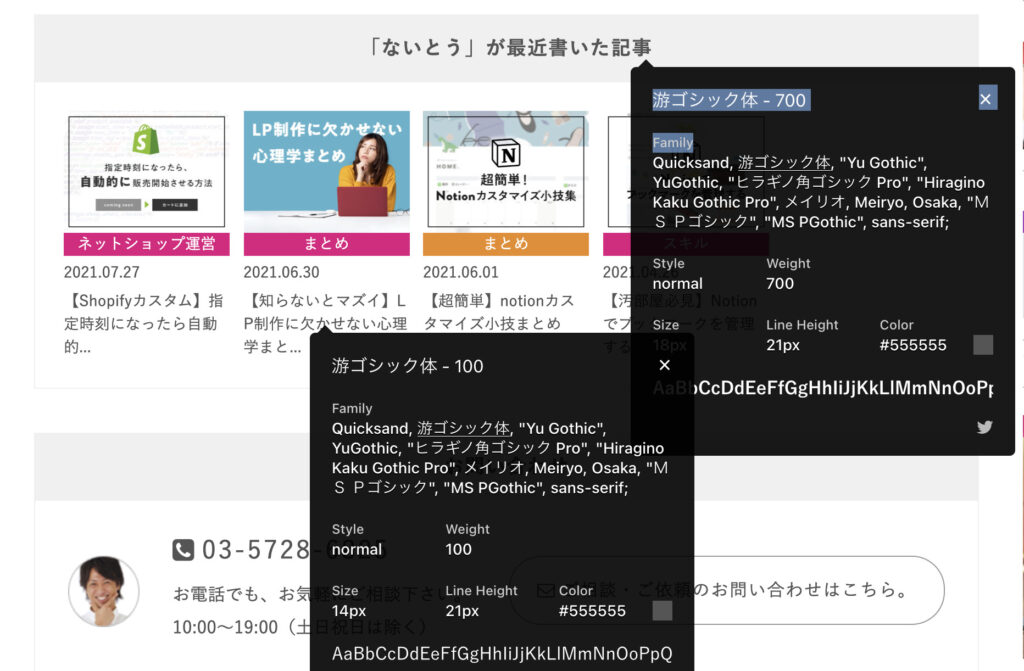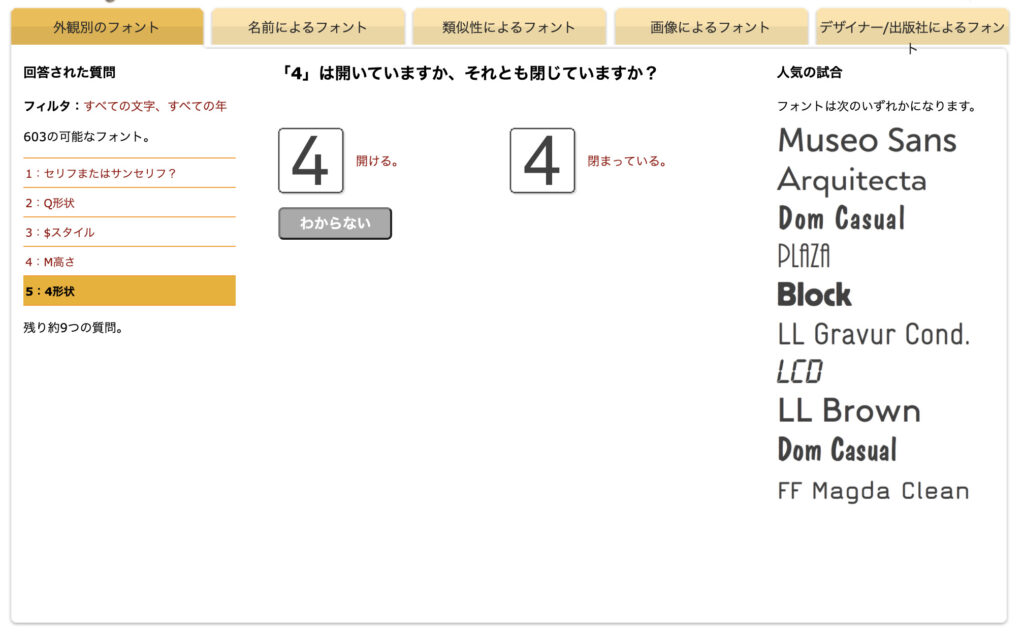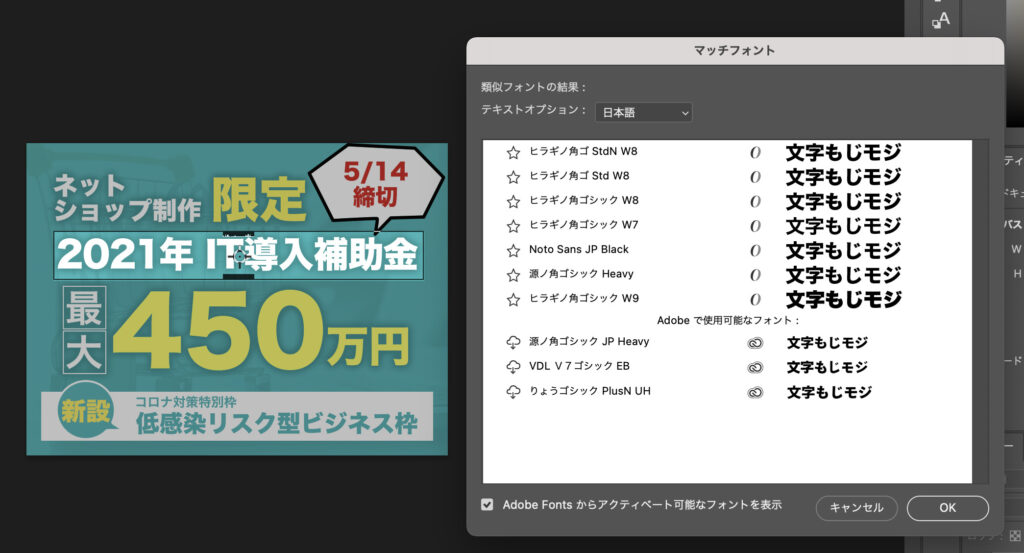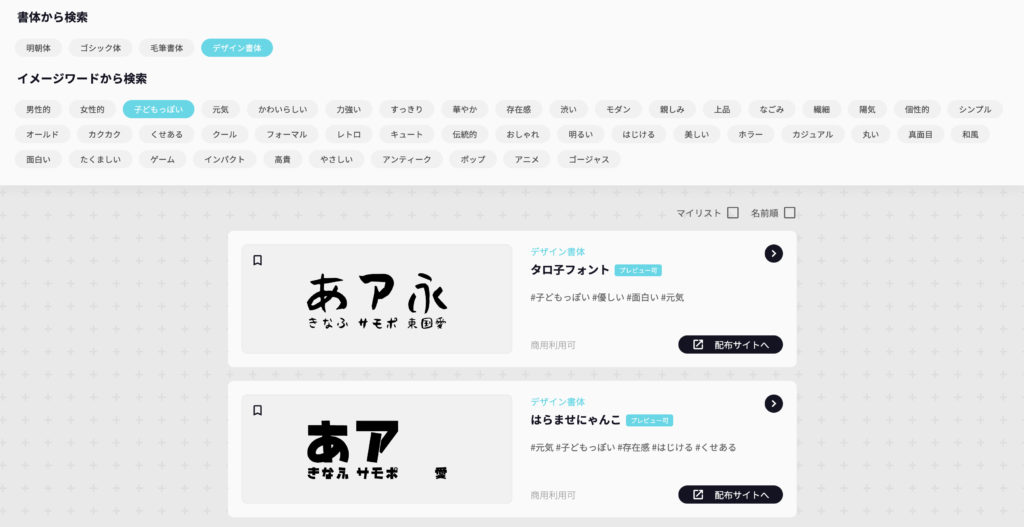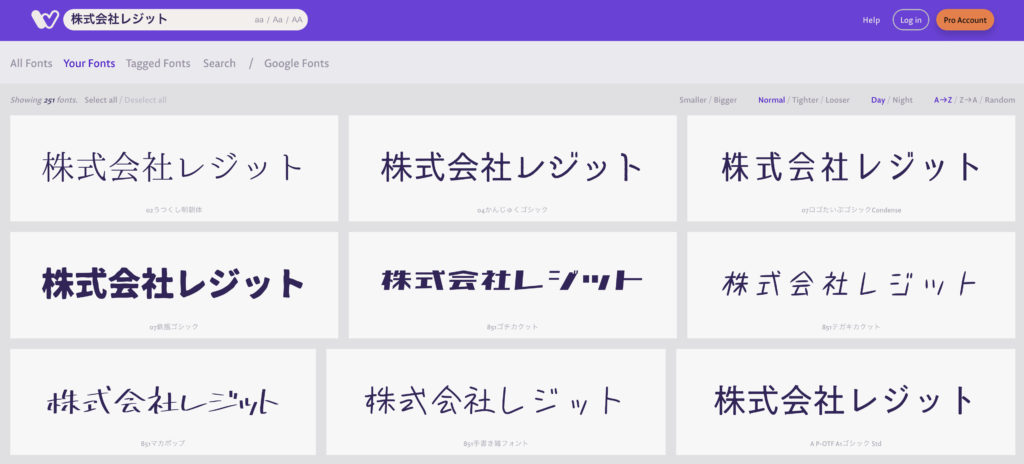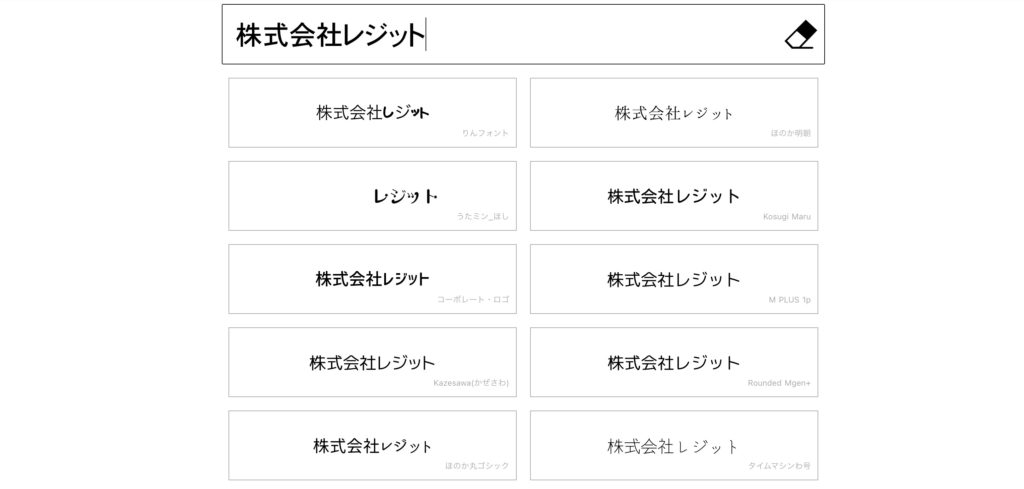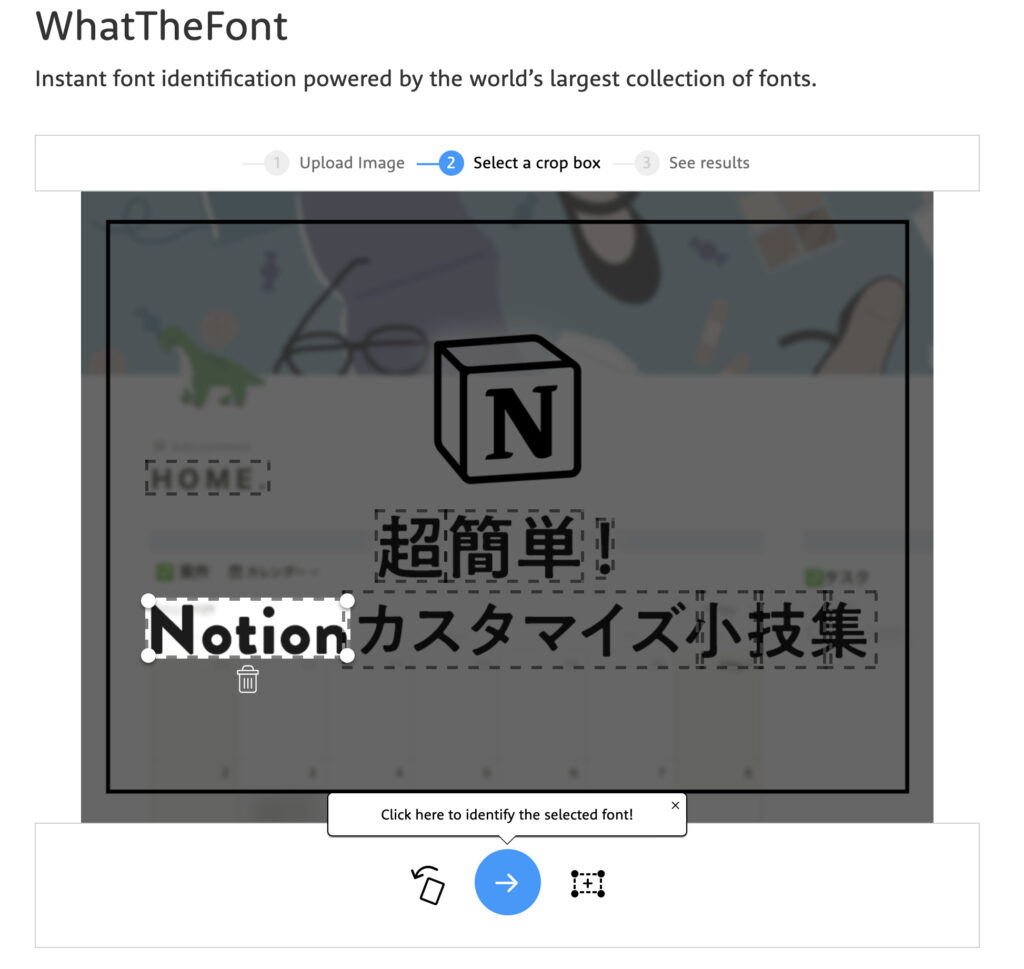
フォントを検索・特定する方法|画像・Webサイト・日本語の調べ方
フォントを検索・特定するときは、最初に「画像の文字」「Webページの文字」「似た書体を選びたい」のどれかを分けます。画像用の検索ツールと、Webページの文字を調べるツールでは、できることが異なります。
この記事では、2021年公開の内容を編集部が確認し直し、画像検索、ブラウザでの確認、試し書きの使い分けを整理しました。候補が見つからないときの見直し方や、利用前の確認も紹介します。料金、対応言語、ログイン条件は変更されることがあるため、各公式案内も確認してください。
調べたい文字の状態で方法を選ぶ
選択できるテキストならブラウザ、写真やスクリーンショットなら画像検索が出発点です。まだ名前が分からず雰囲気から探したいときは、候補の試し書きを比べます。
| 調べたいもの | 使う方法 | 確認できることの目安 |
|---|---|---|
| 写真・スクリーンショット | WhatTheFont、Photoshop | 画像に近いフォントの候補 |
| Webページのテキスト | WhatFont、Chrome開発者ツール | 指定された書体や実際の表示書体 |
| 日本語の候補を見比べたい | ためしがき等の試し書き | 入力した文字の形と雰囲気 |
画像検索で名前が出ても、元の書体が確定したとは限りません。変形、縁取り、文字間隔などが加わっている可能性もあるため、同じ文字列で照合します。
画像から候補を探す方法
画像の中の文字は、フォント名を含むテキスト情報として調べられないことがあります。まず、文字の形を基に候補を出す方法を試します。
WhatTheFont:画像から名前や似た候補を探す
MyFontsのWhatTheFontは、文字の画像をアップロードしてデータベースの候補と比較するツールです。候補のプレビューで自分の文字列を確認できます。
写真を使う場合は、調べたい文字が大きく、背景と区別できる範囲を選びます。複数の書体が混ざっている画像は、対象を分けて調べる方が比較しやすくなります。検索できる範囲と、フォントを実際に使用するための購入・ライセンス条件は別に確認してください。
Photoshopのマッチフォント:編集作業の中で候補を探す
Photoshopの公式案内では、画像内の文字を長方形選択ツールで選び、「テキスト/マッチフォント」から類似フォントを表示する手順が紹介されています。画面表記はアプリのバージョンや言語によって確認してください。
対象の書体が必ず特定できるわけではありません。対応範囲と候補を実際の画像で確認し、見つからなければ試し書きや制作者への確認へ進みます。
Webページのフォントを調べる方法
ブラウザ上の選択できる文字は、CSSや描画情報から調べられます。画像化された見出しやロゴは、同じ方法で特定できない点に注意します。
WhatFont:文字にカーソルを合わせて調べる
Chrome拡張機能のWhatFontは、Webページの文字にカーソルを合わせたり、クリックしたりして書体やスタイルを確認するツールです。
Chrome開発者ツール:指定と実際の表示を分ける
Chromeでは対象の文字を検証し、ElementsのComputedから表示に関する情報を調べられます。Rendered Fontsでは、選択した要素に使われた書体を確認できます。
CSSのfont-familyに複数の名前が並んでいるとき、先頭の書体がすべての文字に使われているとは限りません。日本語と英数字で別の書体が表示されることもあるため、調べたい文字を含む範囲を確認します。
| 見る情報 | 使いどころ |
|---|---|
| font-family | ページ側の指定や代替候補を調べる |
| font-weight・font-size | 太さや大きさの違いを確かめる |
| Rendered Fonts | その要素で実際に使われた書体を確認する |
日本語は同じ文字列で試し書きする
名前の候補が出たら、実際に使いたい日本語で比べます。ひらがな、カタカナ、漢字、英数字のどれかだけが似ていても、文章全体の印象は異なることがあります。
「ためしがき」は、日本語のフリーフォントを探すためのサイトとして公開されています。候補の比較先の一つとして使い、採用時には各フォントの配布元と利用条件も確認します。試し書きサイトに掲載されていることだけで、用途を問わず利用できるとは判断しません。
候補を照合するときは、次の点を見比べてください。
- 使いたい漢字や記号が収録されているか
- 同じ文字列を同じ程度の大きさで並べたか
- 縦線・横線の太さ、文字のふところが近いか
- はね・はらい・終筆の形が近いか
- 句読点と英数字のバランスが合うか
- 太さや字間を調整しただけの違いではないか
特定できないときの確認順
一つのツールで候補が出ないことだけで、特殊なフォントだと決める必要はありません。画像の条件、検索対象、文字自体の加工を順に確認します。
- 文字が小さすぎないか、傾きや背景で形が読みにくくないか確認する
- 複数の書体が混ざっていれば、調べる部分を分ける
- 日本語と英数字を分けて候補を照合する
- 太さ・字間・変形の違いを確認する
- ロゴや独自に描かれた文字なら、制作者や元データの管理者へ確認する
生成AIに候補を尋ねる場合も、提示された名前だけで確定しません。実在する書体か、同じ文字がどう表示されるかを配布元などで確認する、という使い方にとどめます。
まとめ
フォントを検索するときは、画像、Webテキスト、候補比較を分けると手順を選びやすくなります。候補を同じ文字列で照合し、最後に利用条件まで確認してください。